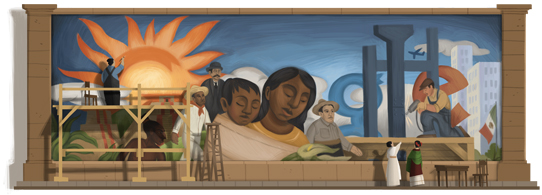
Google's Doodle
จะบอกว่ามันเป็น png ที่ไม่โปร่งใสด้วย น่าเกลียดมาก พื้นขาวๆ :30:
Diego Rivera's 125th Birthday.  :33:
Robert Noyce's 84th Birthday
:25: ชอบตรงมีเพลง
ชอบสีสไตล์นี้จัง :22:
Happy New Year Series   :12: